Кириллическая «ї» в шрифте: как выстроить две точки и ритм строки
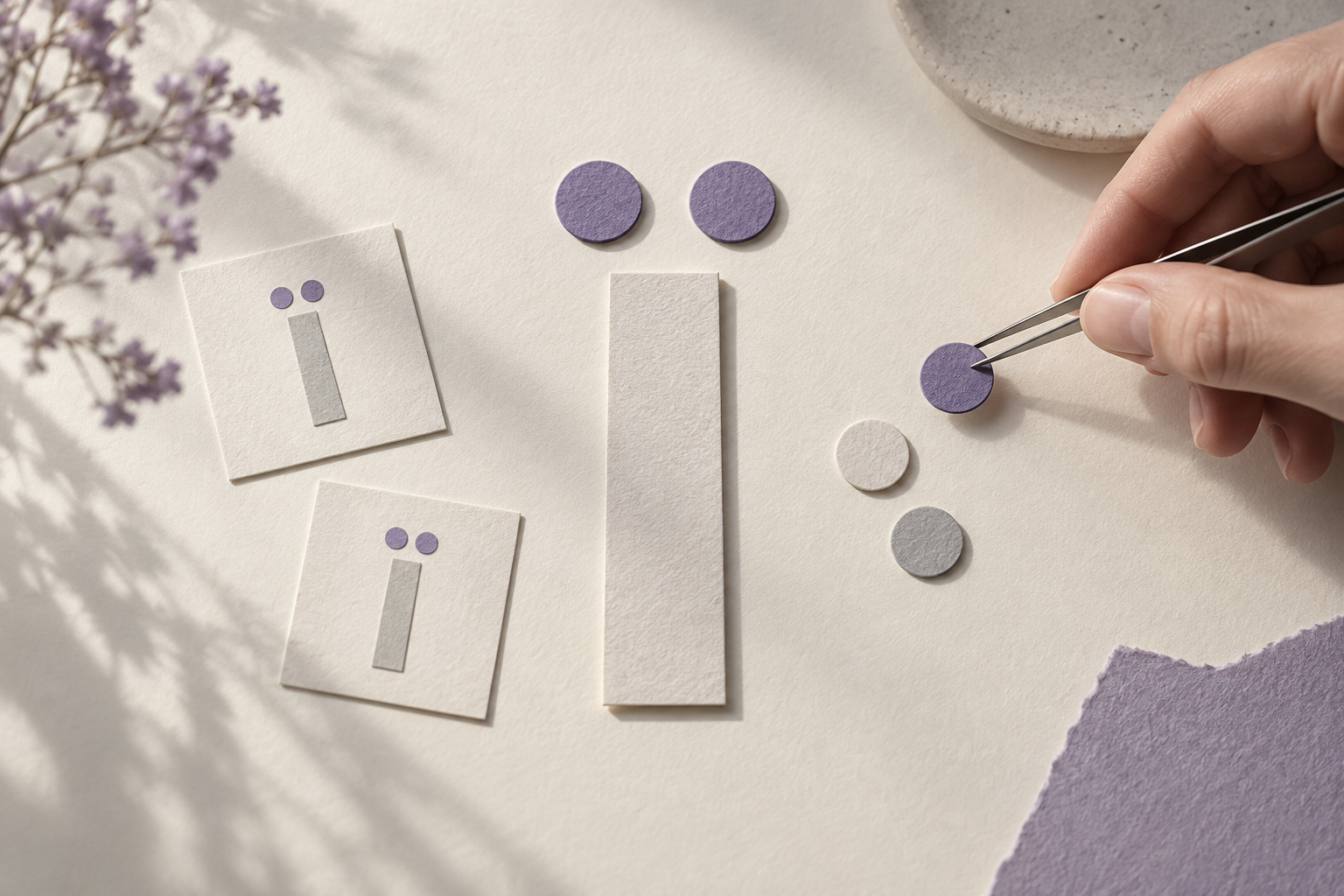
Кириллическая «ї» — самостоятельная украинская буква, а не латинская i с украшением и не случайное сочетание символов. В шрифте важно одновременно сохранить узнаваемую пару точек, согласовать их с рисунком «і» и проверить букву в настоящих словах. Ниже — практический порядок проектирования и проверки, который помогает избежать проблем в наборе, экспорте и подстановке шрифтов.
Что именно нужно нарисовать
В Unicode строчная «ї» имеет код U+0457, а прописная «Ї» — U+0407. В справочнике Unicode строчная форма описана как канонически эквивалентная последовательности кириллической «і» U+0456 и комбинируемого диэрезиса U+0308. Это описание кодирования текста, а не требование рисовать букву как две независимые детали: в шрифте дизайнер задаёт законченный глиф, который должен выглядеть цельно и в строке, и в крупном заголовке. Проверять нужно и готовый символ, и поведение приложения с нормализованным текстом.
Практический ориентир — связь с «і»: основной вертикальный штрих и нижняя часть должны принадлежать той же графической системе, что и соседняя буква, а пара точек делает знак отличимым. Не следует копировать латинскую «ï» и просто менять название глифа. У латиницы другой алфавитный контекст, а у украинской «ї» есть своя прописная форма и соседние буквы, на фоне которых она должна сохранять кириллический характер.
Пара точек: форма, вес и оптическое положение
Сначала определите, какие точки уже есть у «і» в выбранном рисунке: круглые, квадратные, ромбовидные, каплевидные или нарисованные тем же инструментом, что и остальные штрихи. В «ї» разумно сохранить их форму и вес. Если базовая «і» имеет круглую точку, две точки «ї» обычно строят как родственную пару, а не как произвольный знак умлаута, взятый из латиницы.
Расстояние между точками оценивайте по силуэту целой буквы. Слишком тесная пара сливается в пятно на малом кегле; слишком широкая похожа на две отдельные отметки и визуально распадается. Сравните просвет между точками с толщиной основного штриха, внутренними просветами других букв и обычным расстоянием между близкими округлыми элементами. Это не универсальная формула: оптический результат зависит от контраста, размера и того, насколько крупными или мелкими выглядят точки в конкретной гарнитуре.
Положение пары лучше проверять не только линейкой. Геометрический центр основы «і» может не совпадать с воспринимаемым центром всей буквы, особенно если рядом в слове стоит широкая или наклонная форма. Сделайте сначала механически центрированную версию, затем сравните её с вариантом, сдвинутым на небольшую величину влево или вправо. Смотрите на «ї» отдельно и на слова целиком: именно строка покажет, выглядит ли верхний акцент частью буквы.
У прописной «Ї» проверьте соотношение точек с высотой прописных и верхней зоной строки. Увеличивать точки пропорционально телу буквы необязательно: при одинаковом масштабировании они могут стать тяжёлыми. При этом чрезмерно миниатюрные точки исчезнут в вывеске или заголовке на светлом фоне. Сравните прописную с «І», «Ї» в соседних словах и другими буквами, у которых есть верхние элементы, если они предусмотрены гарнитурой.
Как связать «ї» с остальным украинским набором
Самый надёжный способ сохранить характер — проектировать не изолированную букву, а маленькую систему. Пара к «і» задаёт базовый штрих, ширину и форму точки; «Ї» проверяет тот же принцип в прописном регистре; слова показывают, как знак ведёт себя между конкретными соседями. Даже если у шрифта пока нет полного украинского набора, проверьте, что основа и точки не выглядят заимствованными из другой гарнитуры.
Соберите короткую строку со словами «їжак», «країна», «Україна», «поїзд», «з’їзд», «мої» и «Її». В ней есть строчная и прописная формы, повтор «ї», сочетания с округлыми и наклонными соседями, а также апостроф. Это не нормативный тестовый корпус, а рабочая проба: она помогает заметить визуальные проблемы. Добавьте ещё слова из реального макета — названия мест, фамилии, заголовки, подписи или интерфейсные сообщения.
Сравнивайте не только «ї» и «і». В наборе рядом могут оказаться латинская «i», «ï» или символ из fallback-шрифта, если часть знаков отсутствует. На первый взгляд несколько точек могут выглядеть похожими, но контраст, ширина, высота и стиль штрихов выдают подстановку. Поставьте слова в предложении, где кириллица и латиница соседствуют, например в названии проекта или веб-адресе. Если одна буква вдруг меняет толщину или высоту, проверьте, какой именно шрифт её отрисовал.
Ширина, интервалы и верхнее пространство
Две точки находятся над основным телом буквы, поэтому при корректном построении обычно не требуют добавлять к боковым метрикам «ї» отдельную ширину. Но визуально верхний силуэт шире. Проверьте, не сталкиваются ли точки с надстрочными знаками и декоративными элементами в соседних строках, заголовках или логотипах. В тесном межстрочном интервале особенно важна высота, зарезервированная для диакритики: если приложение обрезает верх, причина может быть как в метриках строки, так и в метриках шрифта или самом макете.
Удачная «ї» соединяет рисунок «і» с ясной, устойчивой парой точек и сохраняет ритм украинской строки. Проектируйте прописную и строчную формы вместе, проверяйте букву в словах, при малом размере и после экспорта — тогда знак останется узнаваемым и в короткой подписи, и в длинном тексте.